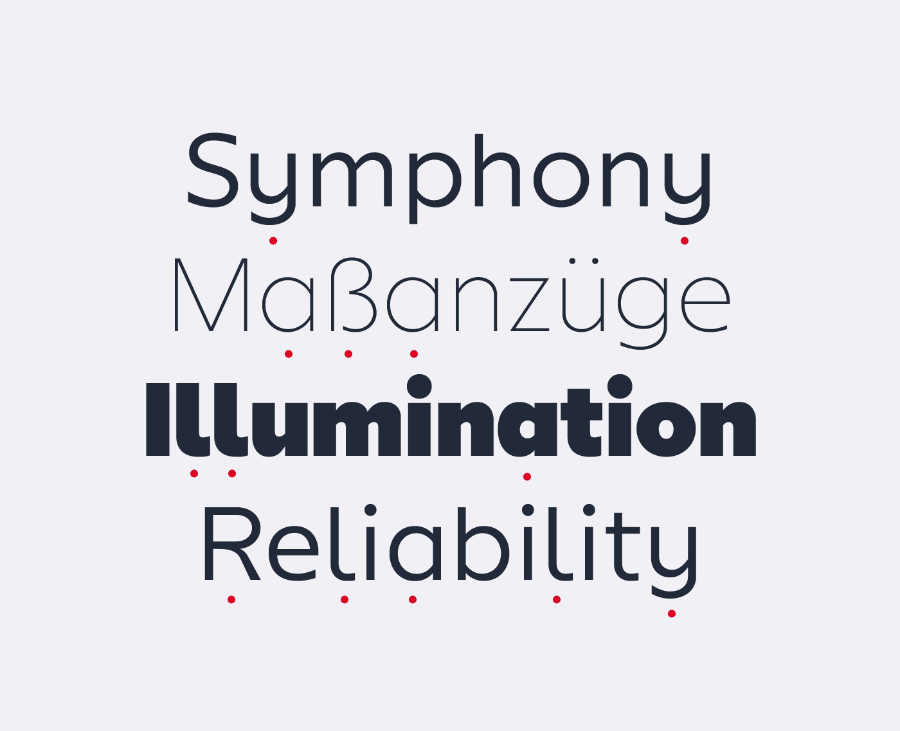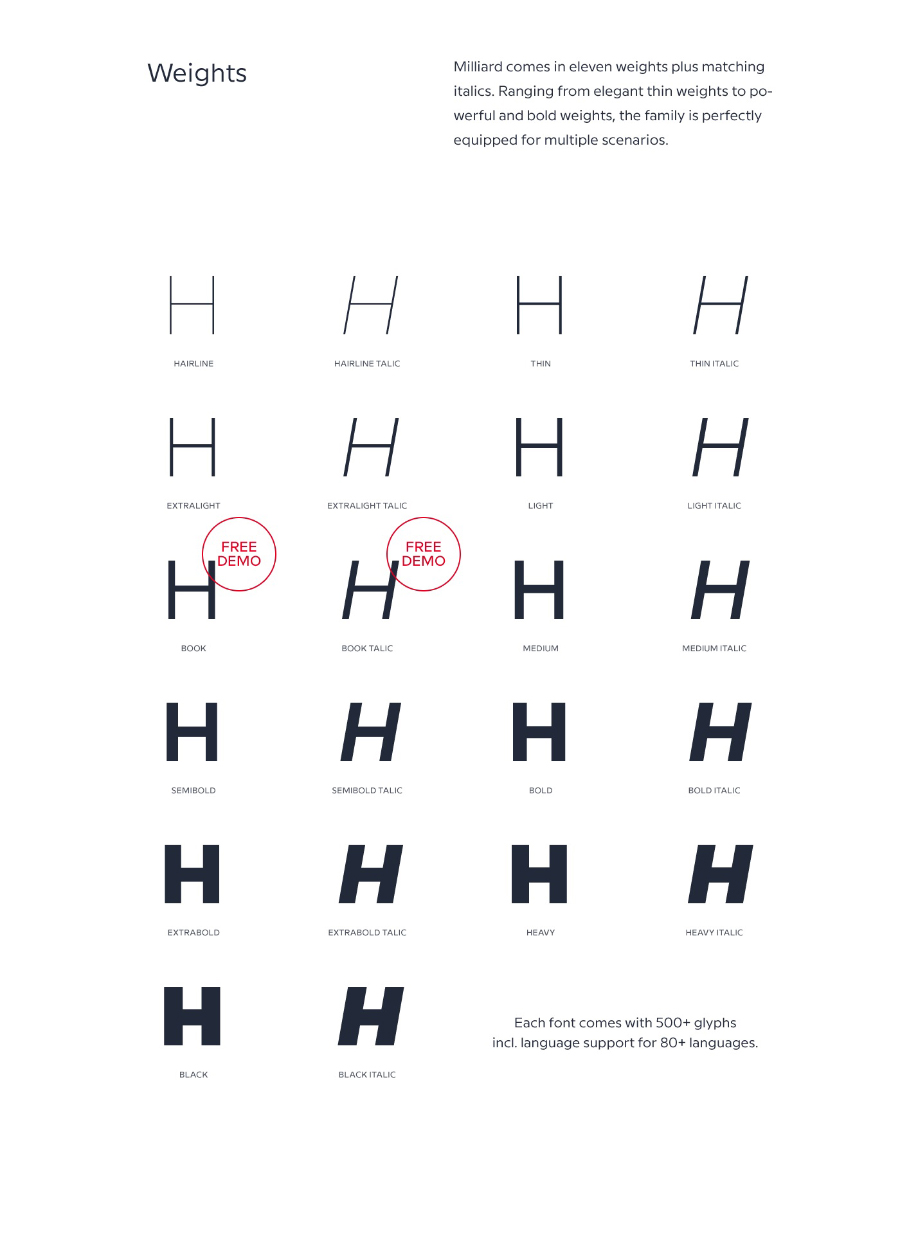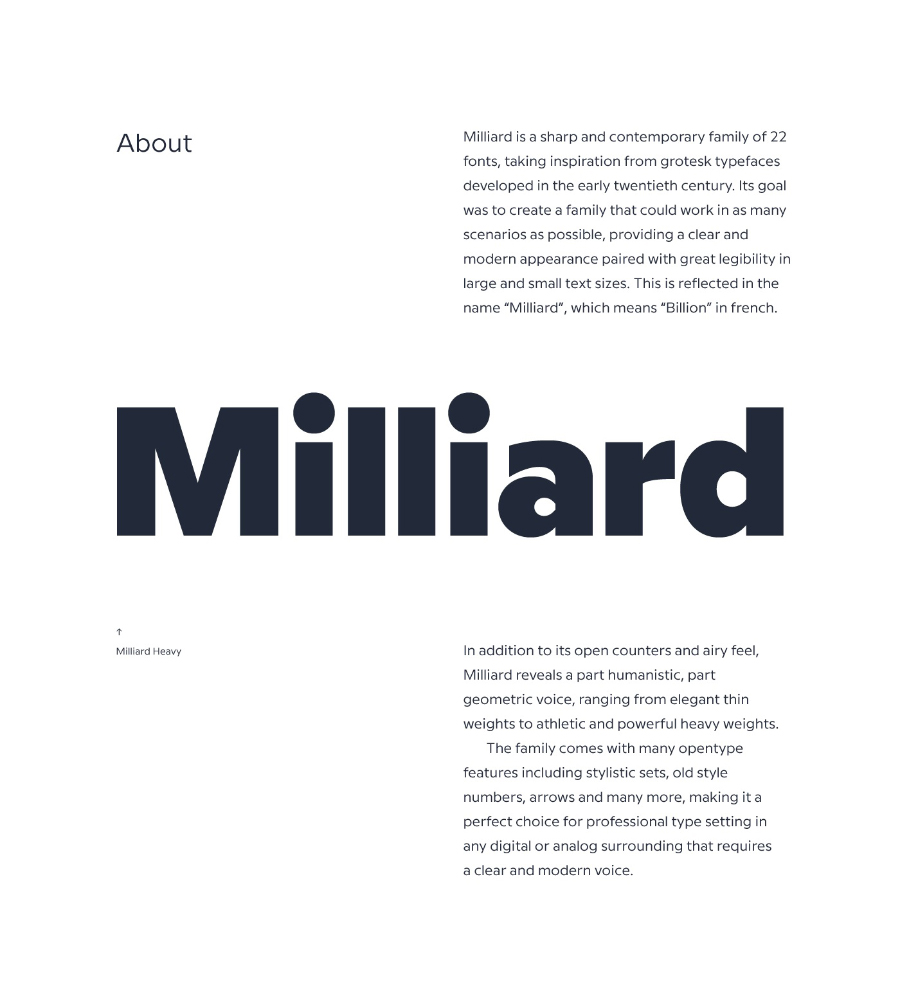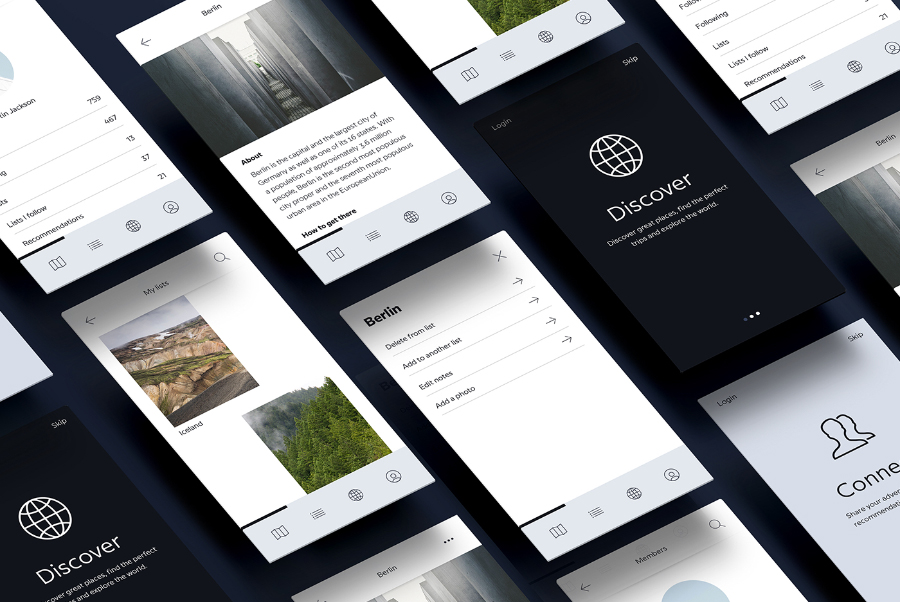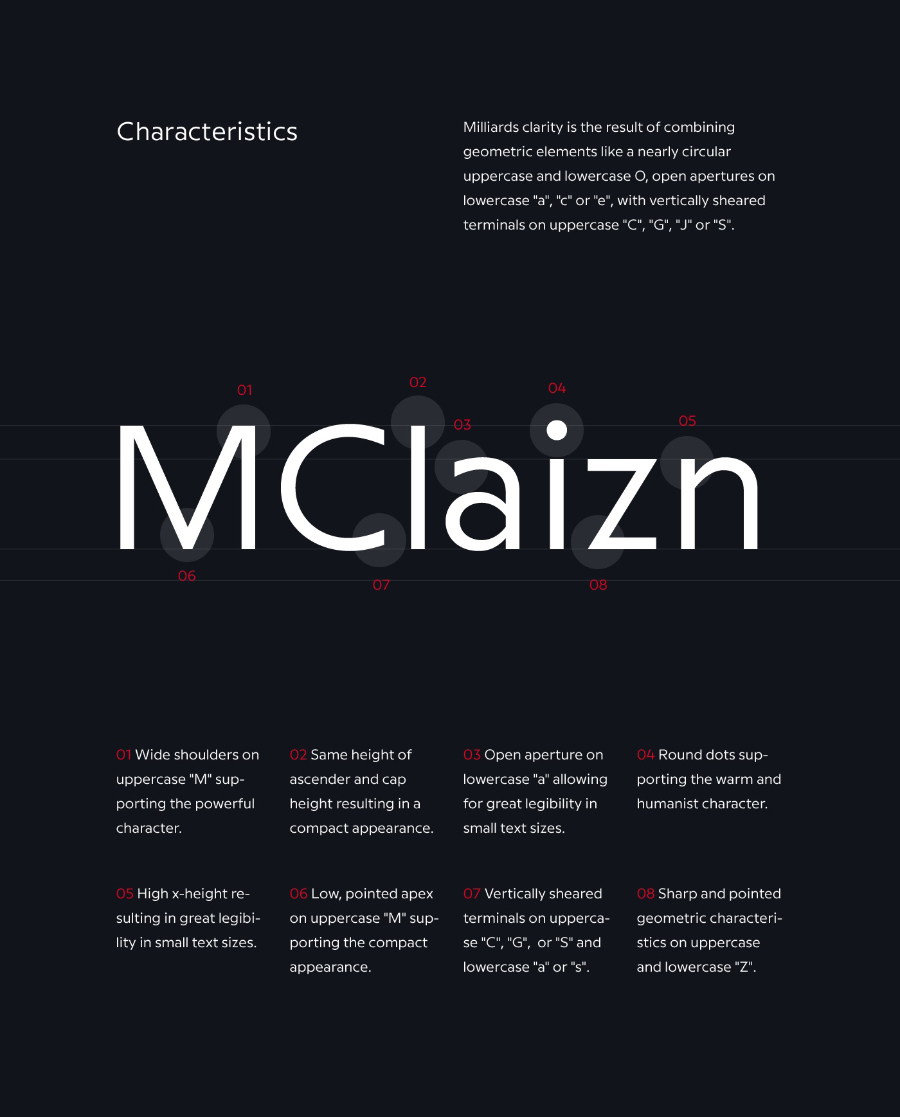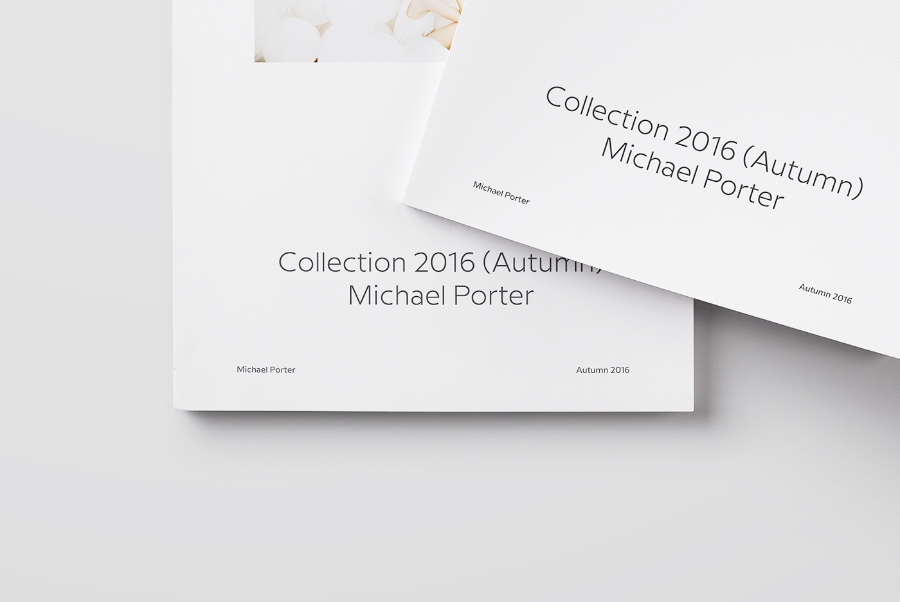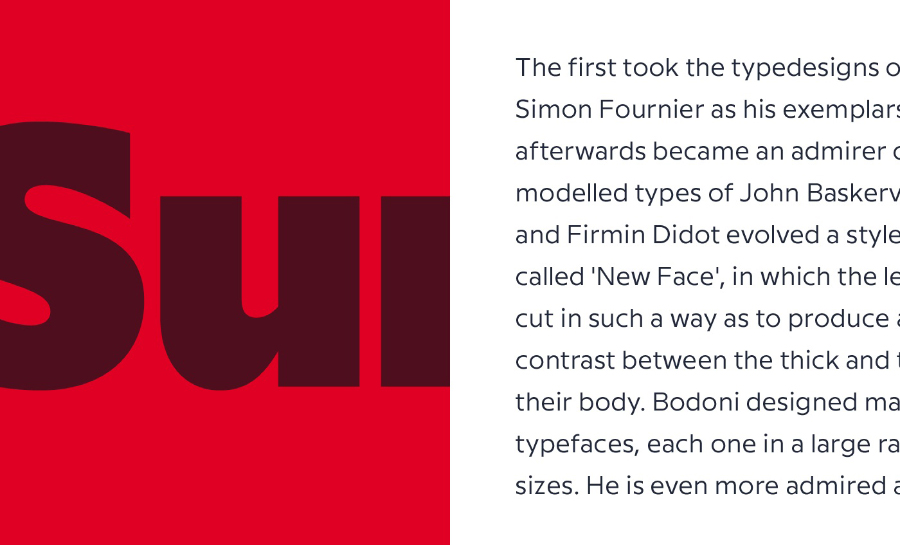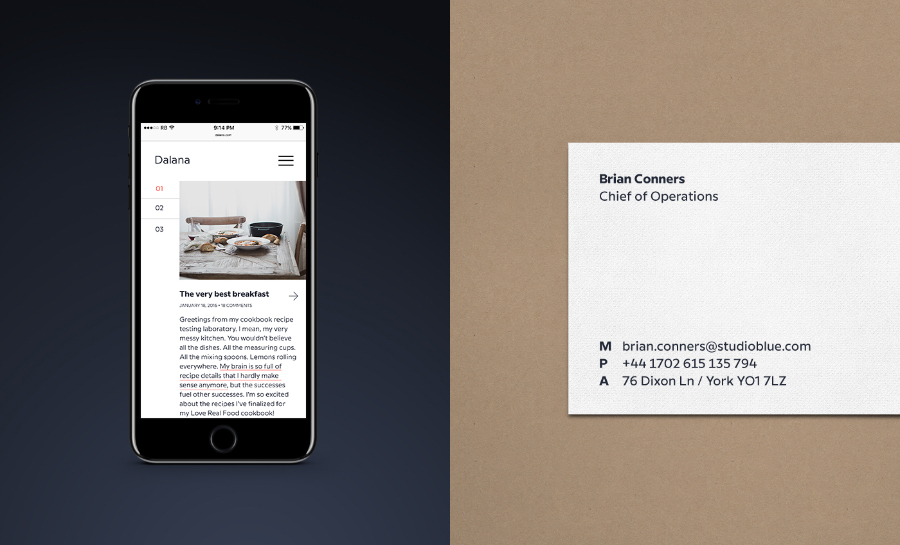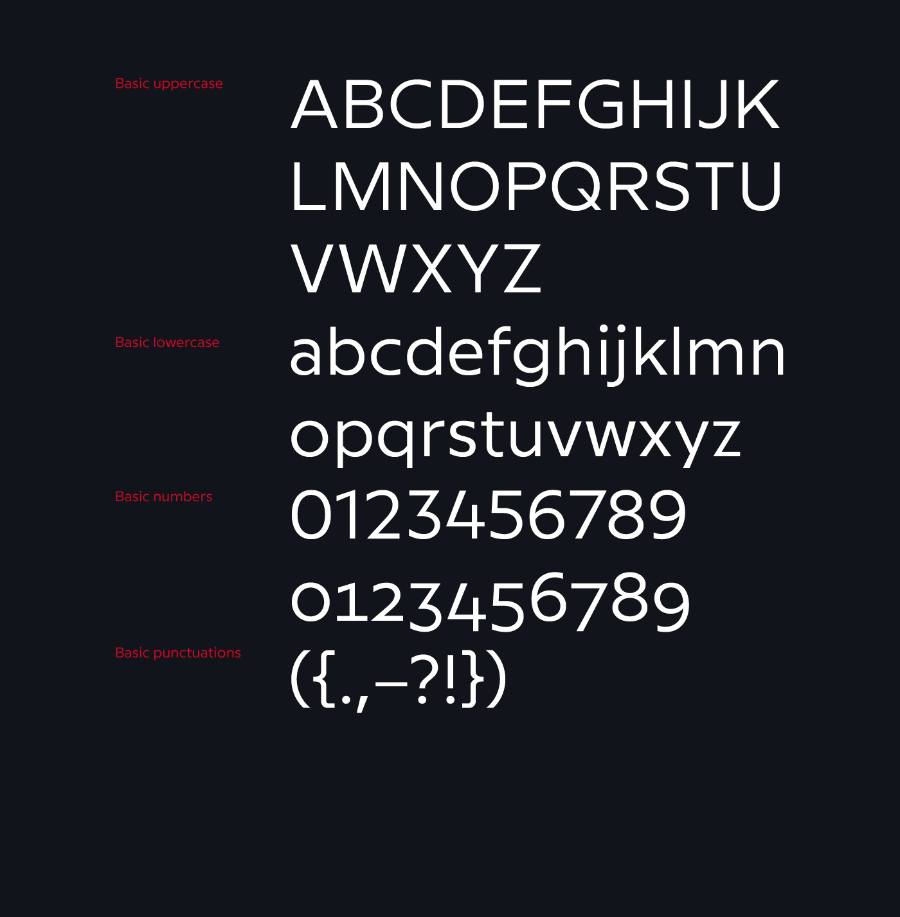
十亿免费演示
Milliard Sans Free Demo是一个免费版本的22个字体的锐利和当代家庭。它从二十世纪初开发的怪诞字体中获得灵感。其小写字母“a”,“c”或“e”的开放计数器使得文本尺寸更小,易于理解。因此,它将支持不显眼,清晰和现代的外观。当在标题设置时,Milliard显露一部分人的,部份几何声音从优雅和开放稀薄的重量到运动和强有力的重量。